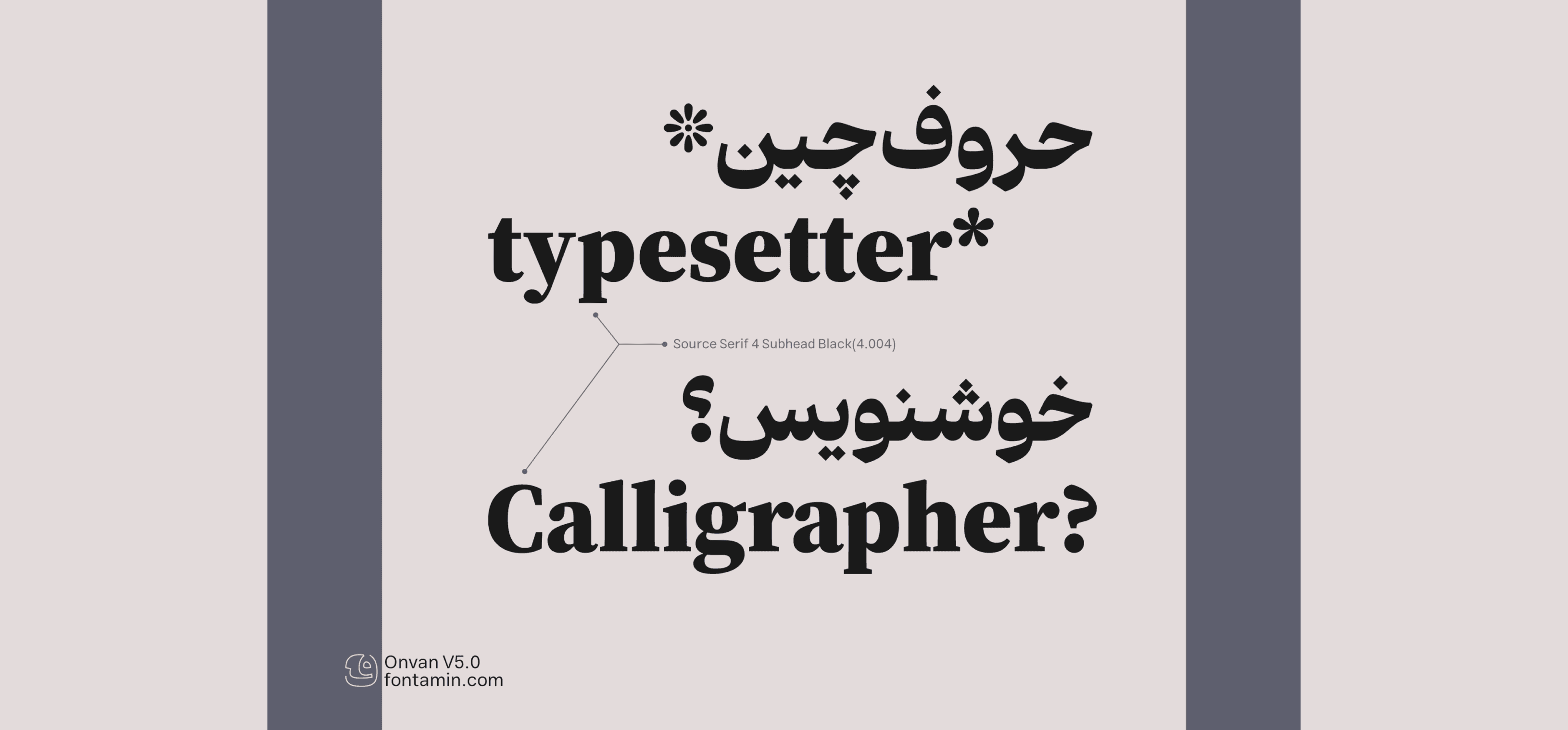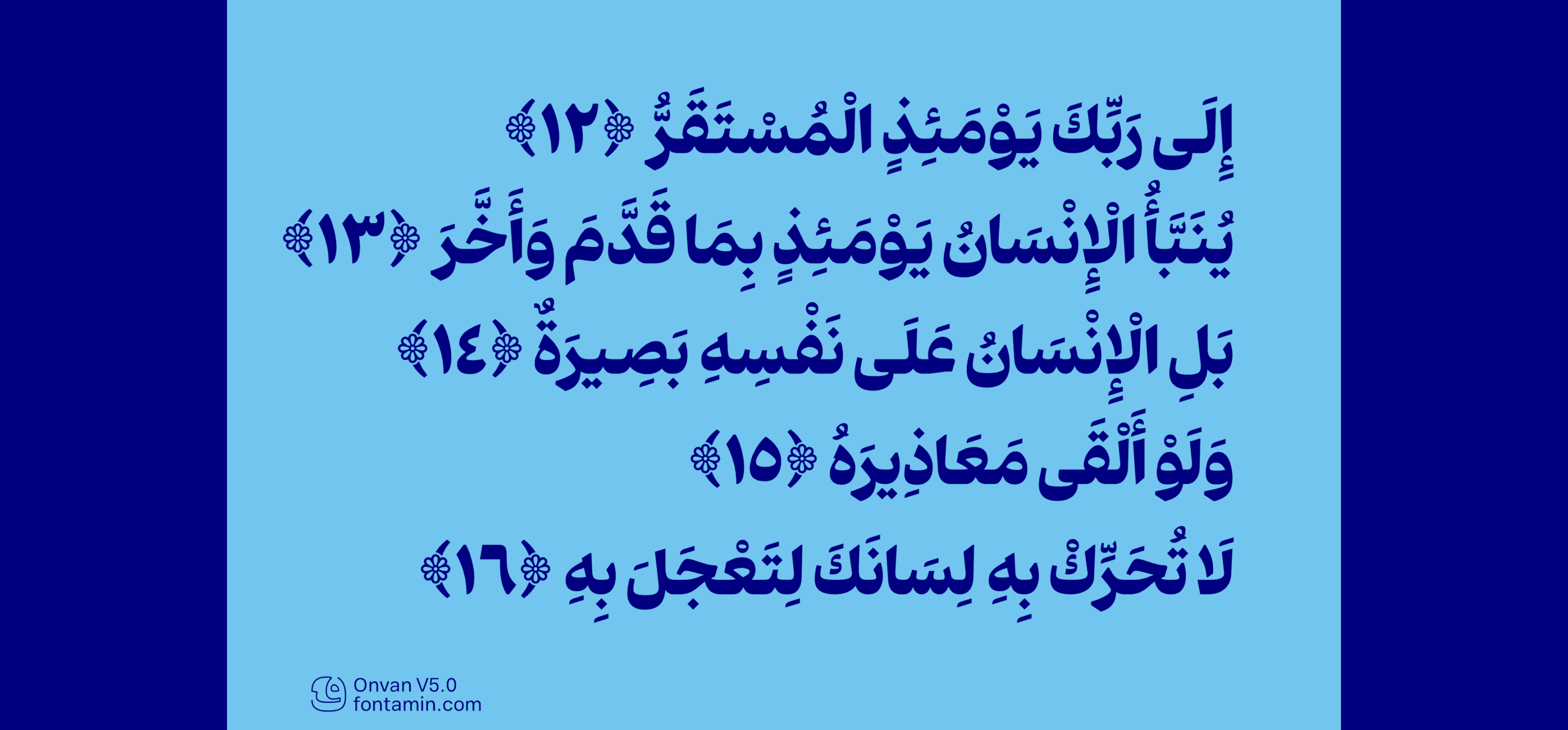
"عنوان" یک خط تيتر فارسي ضخم البنية، أُعيد النظر في تصميمه بما يتناسب مع وظيفته الأساسية كـ خط عرضي (Display Font). رغم أن معظم خطوط العناوين تتميّز بثقل وزنها، فإن خط "عنوان" لا يكتفي بذلك، بل يستخدم أيضًا تكبيرًا مبالغًا في أجزاء الحروف لزيادة التأثير البصري.
هذا النمط من التصميم يجعل "عنوان" خيارًا مثاليًا ليس فقط للعناوين القصيرة، بل أيضًا للعناوين متعددة الأسطر، مما يوسّع من نطاق استخدامه في التصاميم الطباعية والجرافيكية.Ask ChatGPT